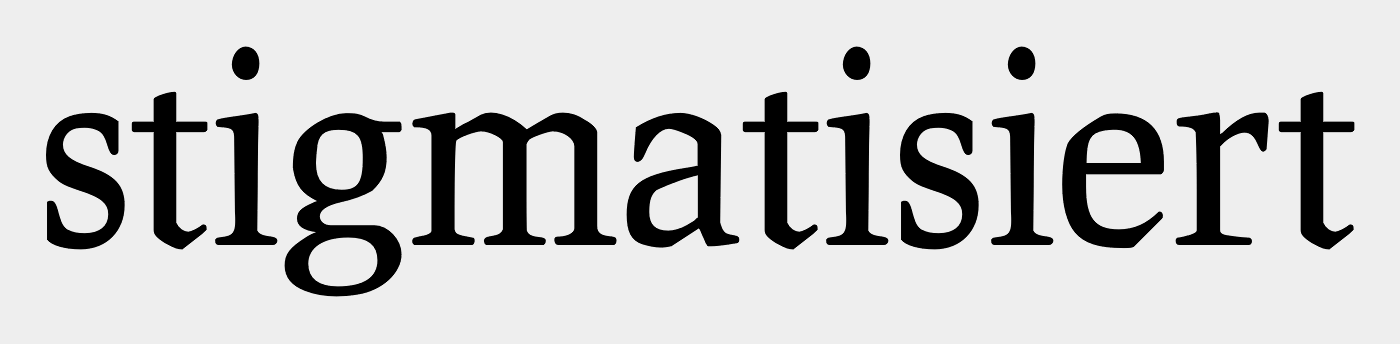
Serifenfont gesucht
Ich bin auf der Suche nach einem ähnlichen Serifenfont wie der Cardamon. Die eckige Anmutung würde super zu einem Projekt passen. Hat irgendwer Alternativvorschläge? Das wäre super.
Zuerst stellt sich natürlich die Frage: Was stört an der Cardamon?
… dafür aber ein sehr schönes ẞ/ß-Paar sowie für das Ungarische sehr gut verwendbare (Doppel-)Akuts. :rockon:
Nur das frakturartige Divis, für das es anscheinend keine Alternativform gibt (selbst nicht auf U+2010), wird die Benutzbarkeit für viele Anwender sicher einschränken. Ob der Autor ;-) sich wohl erweichen könnte, da eine Alternative anzubieten?
…  das frakturartige Divis, für das es anscheinend keine Alternativform gibt … Ob der Autor ;-) sich wohl erweichen könnte, da eine Alternative anzubieten?
Mit der "eckigen Anmutung" meine ich ähnlich wie bei der GT Sectra den kalligrafischen Einfluss mit der Anmutung der Schärfe erzeugt durch ein Skalpellmesser. Sollte ein Serifenfont sein und modern. Danke schon mal für eure Hinweise